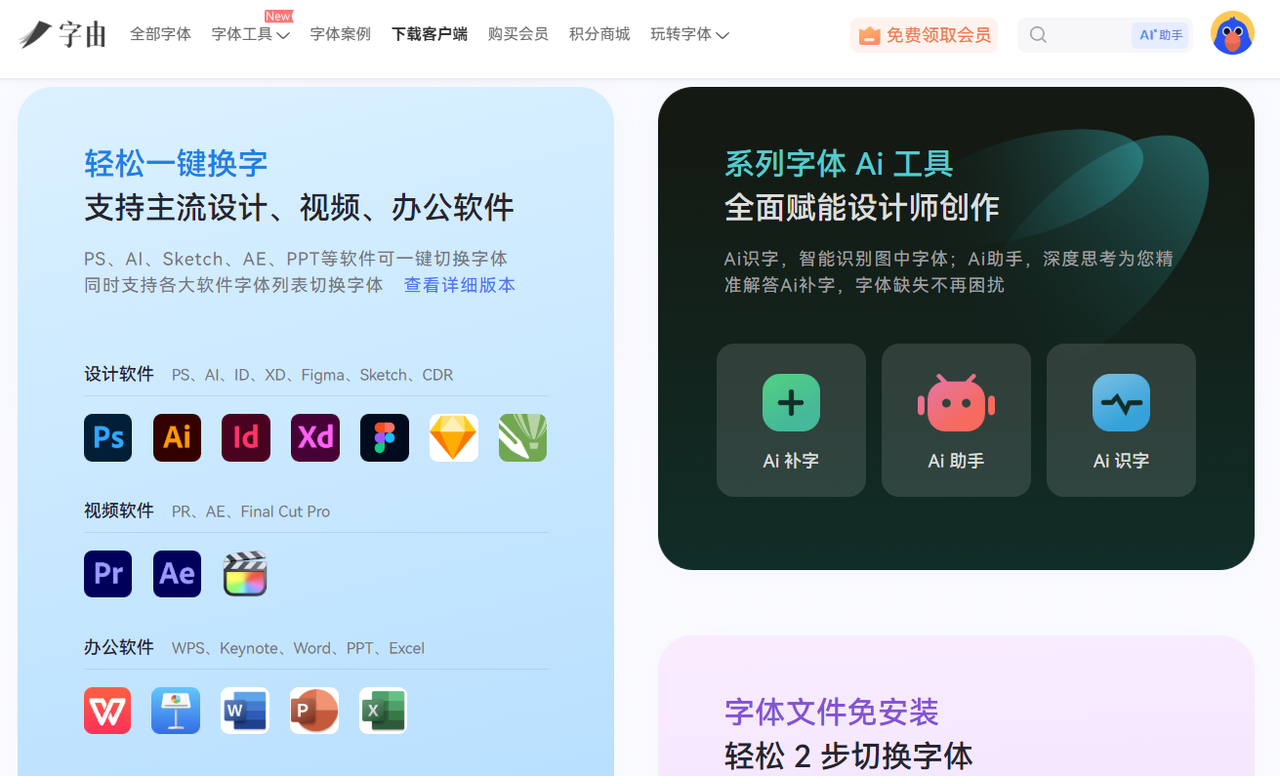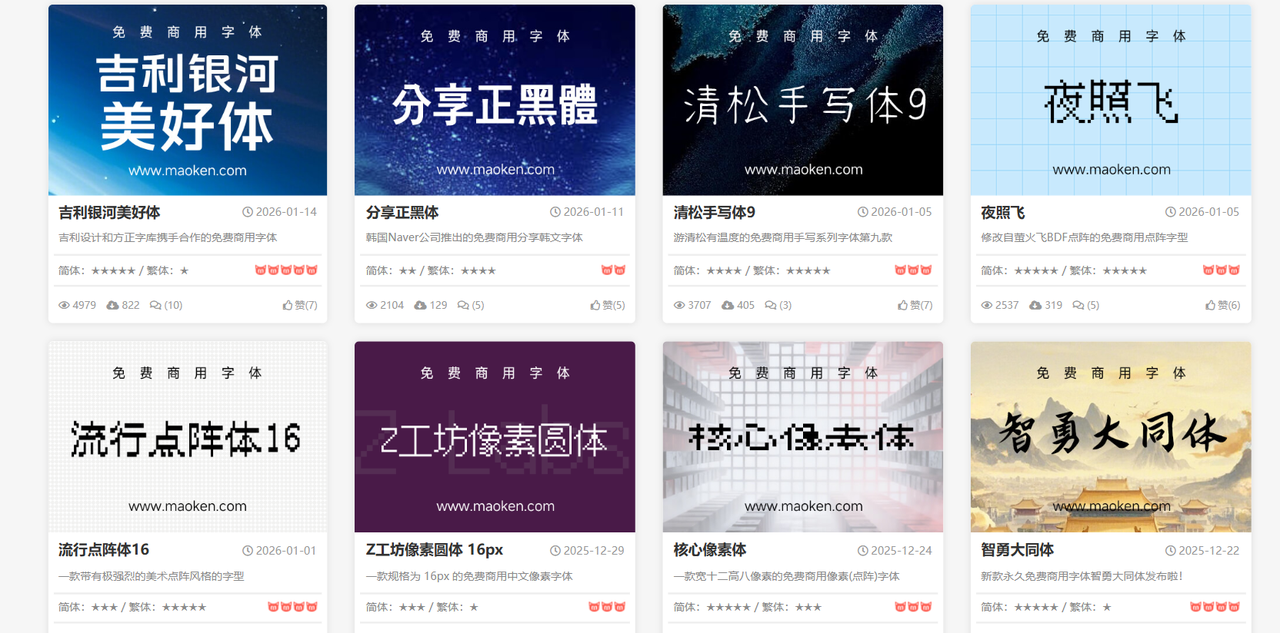
支持免费下载字体的网站有什么?其实市面上这类的字体网站并不少,像国内的字由和猫啃网,国外的 Font Space 和 Fotsly 就非常值得体验一下。其中字由做为一个颇有经验,字体素材也丰富的字体下载网站,迄今已经服务过超百万名专业设计师,如果让我来推荐的话,我肯定想推荐大家先来体验一下这款不能错过的字体网站。接下来,本文就将为你详细介绍一下【字由】的优势在哪里,以及其余也觉得好用的字体下载网站,给大家提供一些新的选择,一起来看看吧!
提到支持免费下载字体的网站,不得不提一下【字由】。字由是一个用字功能成熟,用字经验丰富的字体网站,相信有过字体使用经验的设计师对这个网站不会陌生。而今天之所以给大家推荐字由,也是看中了它站内免费字体多样,字体使用门槛较低的特点。因为很多朋友在接触新的字体网站时,除了会挑这个网站提供的字体素材是否足够支撑完成日常工作时,也会考量一下字体使用步骤是否精简。
而在我看来,字由可以满足以上两点要求。目前字由站内汇集了 10000+ 字体素材,其中 3000+ 字体支持免费商用。像一些思源黑体,思源宋体,阿里妈妈普惠体,阿里妈妈东方楷体等等这些常用字,字由站内均有免费提供。在此基础上,字由站内还有其他类型的免费字体,而且不仅仅是中文,字由还提供了英文,日文,韩文以及泰文,阿拉伯文等多种语言的字体。这 3000+ 免费的字体基本上可以覆盖日常设计工作中的用字需求,在【字由】站内,可一站式解决多种用字需求。
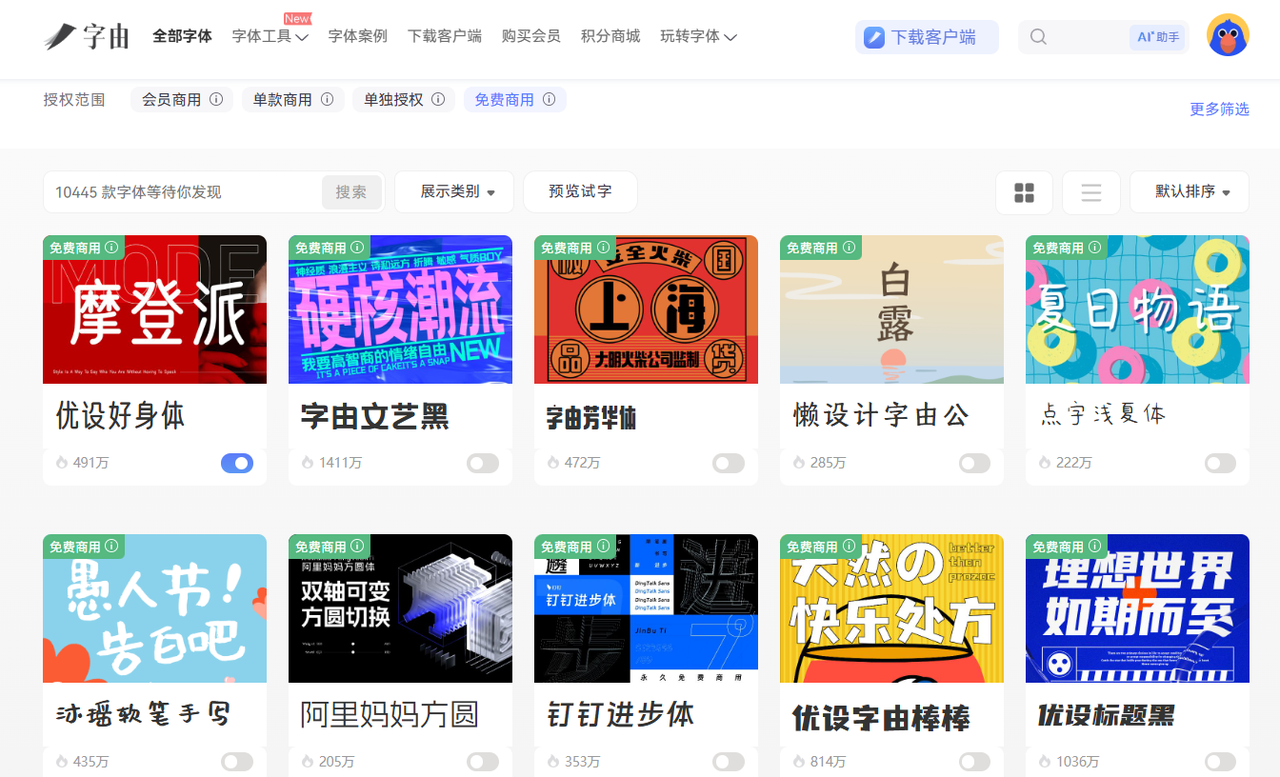
2、猫啃网:700+ 免费中文字体,无版权字体免费下载
猫啃网是一个开源的字体网站,它站内汇集的字体素材几乎全部支持免费下载,而且字体更新速度也很及时,你甚至可以把它当做一个获取免费字体资讯的工具使用。猫啃网站内还将免费字体以语言做了分类,在访问官网后在导航栏中就可以看到。
猫啃网中提供了免费中文,西文,日文和韩文,有多语言用字需求的可以看一下【字由】,也能看一下猫啃网。猫啃网提供的字体拥有正版授权,点进字体详情页后可以清楚看到授权声明,可以放心使用站内的字体。
3、Font Space:专为设计师打造的字体下载网站
Font Space 是一个专为设计师打造的字体下载网站,它站内提供的英文字体居多,而且风格十分多变,除了日常用到的比较偏 “正式” 的字体风格之外,站内还提供了比较活泼,更具有创意的艺术字体、如果要做游戏类 UI 界面设计或者比较时尚现代的海报,可以来 Font Space 中找一下英文字体。
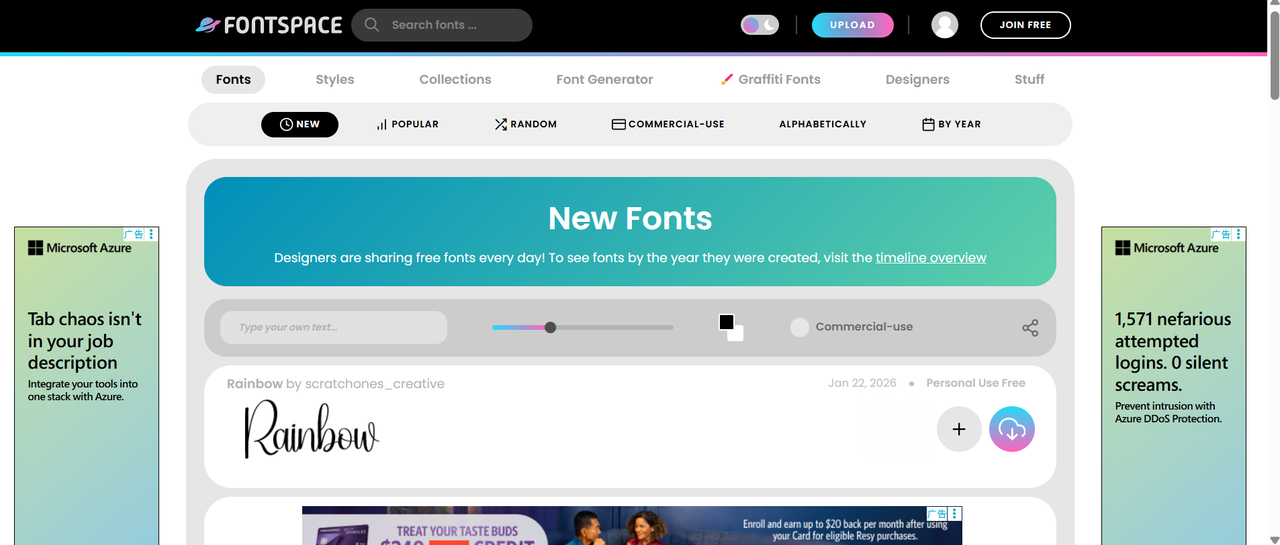
4、Fontsly:高质量免费字体下载网站,提供字体预览
Fontsly 也是一个十分不错的字体下载网站,它同 Font Space 一样,主要提供英文字体素材。Fontsly 站内的提供的字体风格主要包括衬线字体,非衬线字体,书法字,卡通字等等,日常英文用字使用 Fontsly 也是个不错的选择。
Fontsly 还提供了一个比较有意思的字体预览功能,像一般的字体网站在提供字体预览效果时,可能只提供文本效果的预览,而 Fontsly 还加入了 “颜色” 这个选项。在字体界面,Fontsly 提供了色环,可以在其中取色,然后 “Update” 就可以预览字体颜色的设计效果了。